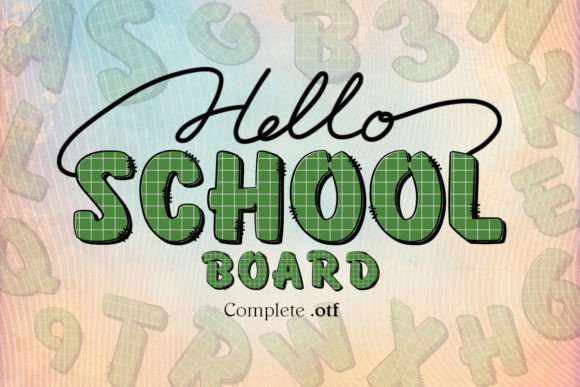
School Board
School Boardのような高品質の素材をお探しの場合、このプレミアムパッケージはクリエイティブなプロジェクトに素晴らしい選択です。
精密に作られたSchool Boardは、クリーンなベクター、滑らかなタイポグラフィ、そして安心のための商用ライセンスを提供します。
POD(オンデマンド印刷)製品、結婚式の招待状、またはソーシャルメディアのグラフィックを作成している場合でも、School Boardは理想的です。